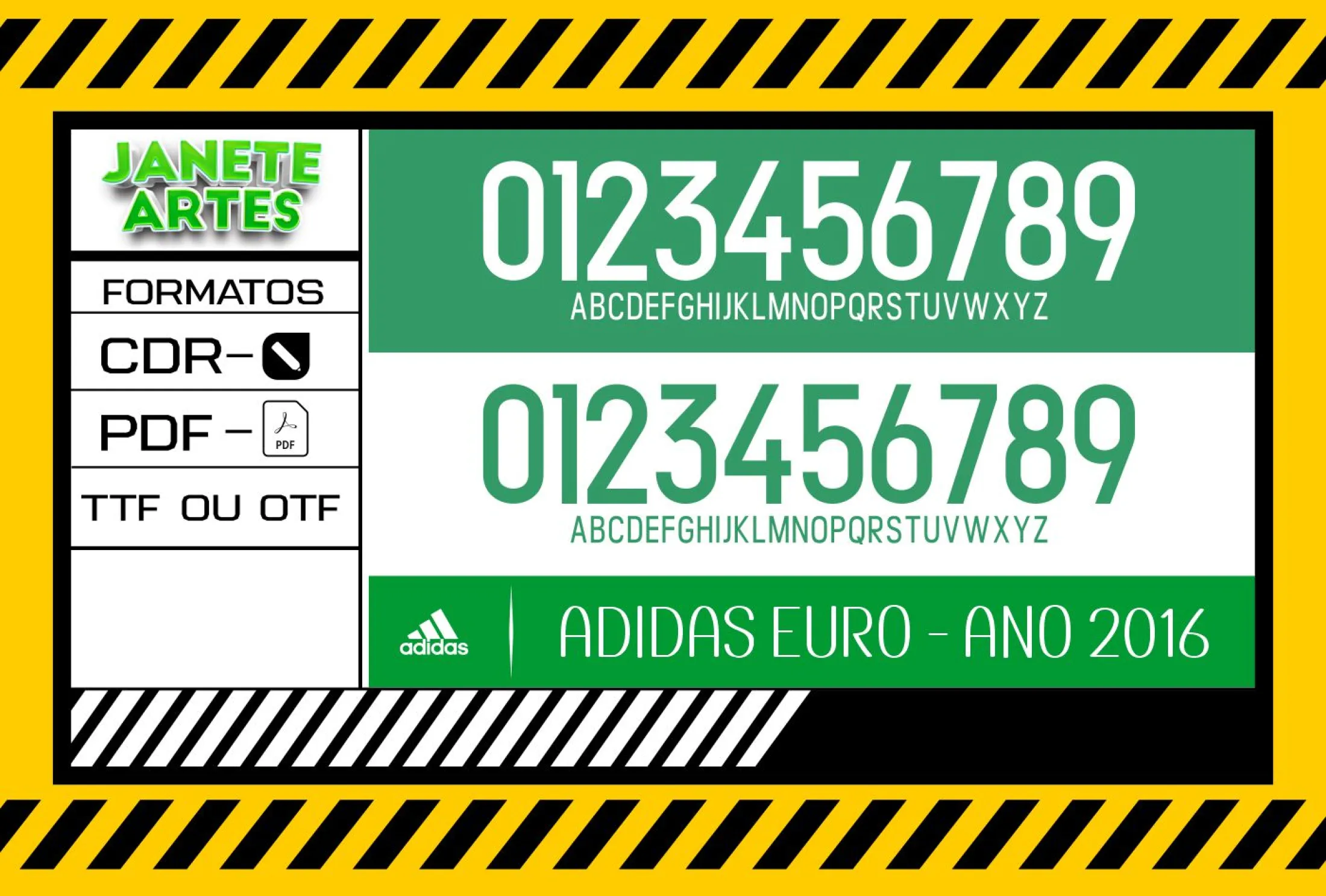
Fonte de Time Tipografia Adidas Euro 2026
Conheça o arquivo Fonte de Time Tipografia Adidas Euro 2026 ideal para personalizar camisetas com o estilo e personalidade do maior evento europeu de futebol. Versátil e exclusivo para fãs e apaixonados.
Uma história para os fãs apaixonados
Imagine um grupo de amigos, todos apaixonados por futebol, tentando encontrar uma forma de marcar suas memórias no Euro 2026. Eles queriam camisetas que realmente mostrassem a alma do evento, aquela tipografia icônica da Adidas que dá um toque especial ao uniforme. Ao encontrar o Arte Camiseta Fonte Tipografia Time Adidas Euro 2026, viram a chance perfeita para criar peças personalizadas, únicas e com aquele estilo que ninguém mais tem. A emoção deles ao vestir essas camisetas na final foi simplesmente inesquecível!
• Fonte tipográfica oficial usada nos times Adidas do Euro 2026, para personalizar camisetas, camisas e blusas.